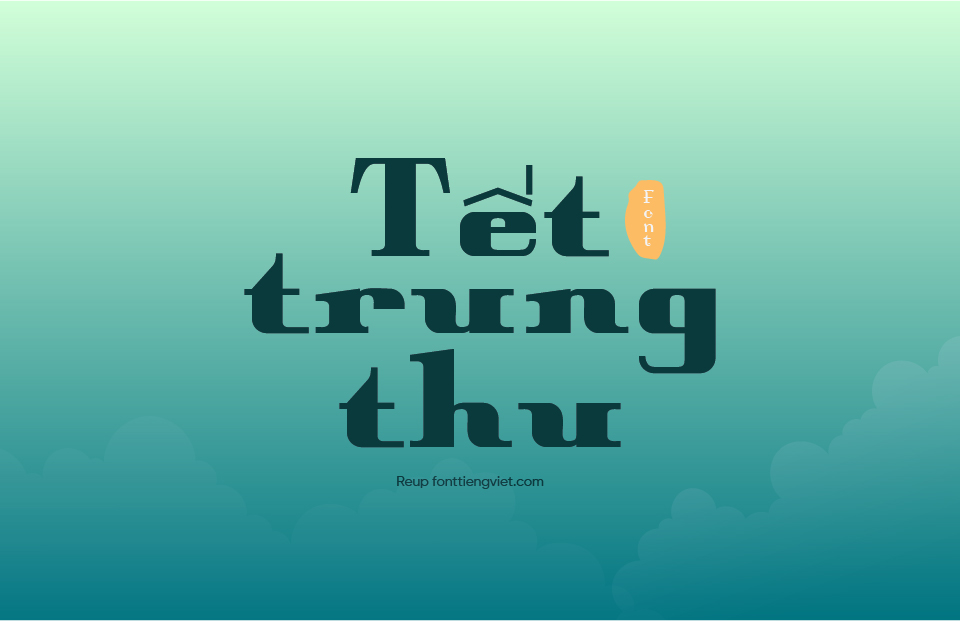
Chia Sẻ Font Việt Hóa LNTH Peter Obscure – Nét Chữ Cổ Tích Cho Đêm Hội Trăng Rằm
Mùa Trung Thu không chỉ là tết đoàn viên mà còn là thế giới của những câu chuyện cổ tích về chú Cuội, chị Hằng và những đêm rước đèn đầy màu sắc. Nếu bạn đang tìm kiếm một phông chữ có khả năng kể chuyện, mang chút âm hưởng ma mị, huyền bí nhưng vẫn giữ được nét đáng yêu, thì Font Việt hóa LNTH Peter Obscure chính là mảnh ghép hoàn hảo cho dự án thiết kế sắp tới.
Khám phá vẻ đẹp của Font LNTH Peter Obscure
Peter Obscure là một typeface vô cùng đặc biệt. Khác với những nét chữ thanh lịch thông thường hay những nét cọ bụi bặm, bộ font này mang hơi hướng của những cuốn truyện tranh cổ tích phương Tây (storybook style). Các con chữ được thiết kế với tỷ lệ độc đáo, những đường cong uốn lượn bất quy tắc tạo nên một tổng thể vừa tinh nghịch, vừa có chút bí ẩn (obscure).
Nhờ bàn tay tài hoa của đội ngũ LNTH, bản Việt hóa đã thổi hồn trọn vẹn vào các ký tự tiếng Việt. Các dấu câu được tinh chỉnh tỉ mỉ, hòa quyện tự nhiên với đường nét phá cách của chữ gốc, giúp các designer dễ dàng truyền tải thông điệp bằng tiếng mẹ đẻ mà không làm mất đi “chất” riêng của font.
Ứng dụng “cực mượt” cho các thiết kế chủ đề Trung Thu
Với phong cách ma mị và cổ tích, LNTH Peter Obscure sẽ tỏa sáng rực rỡ trong các ấn phẩm mang tính kể chuyện:
• Bao bì bánh Trung Thu cho trẻ em: Cực kỳ phù hợp với các dòng sản phẩm có concept minh họa nhân vật hoạt hình, thế giới thần tiên hoặc các họa tiết động vật ngộ nghĩnh.
• Poster / Thiệp mời sự kiện: Làm tiêu đề chính cho các đêm hội trăng rằm, lễ hội hóa trang hoặc các chương trình nhạc kịch Trung Thu, tạo sự tò mò và thích thú cho người xem.
• Thiết kế Social Media: Tạo điểm nhấn cho các bài post kể chuyện sự tích đêm rằm, mini-game tương tác trên Fanpage với không khí vui tươi, nhí nhảnh.
Mẹo phối Font (Font Pairing) hoàn hảo
Vì LNTH Peter Obscure là một dạng font trang trí (Display/Decorative font) mang đậm tính cá nhân, nó nên được ưu tiên sử dụng cho các tiêu đề (Headline) hoặc các câu quote ngắn.
Để bản thiết kế cân bằng và dễ đọc, bạn hãy sử dụng UX Builder để kết hợp nó với những font Sans-serif bo tròn nhẹ nhàng (như Nunito, Quicksand hoặc Baloo) cho phần văn bản chi tiết. Sự kết hợp này vừa giữ được nét vui tươi, vừa đảm bảo thông tin được truyền tải rõ ràng.
Lưu ý nhỏ: Hãy thử kết hợp font chữ này với các hiệu ứng Text Effect như viền nổi (Stroke) hoặc đổ bóng (Drop Shadow) trong Photoshop để con chữ trông nổi bật và có chiều sâu hơn nhé!